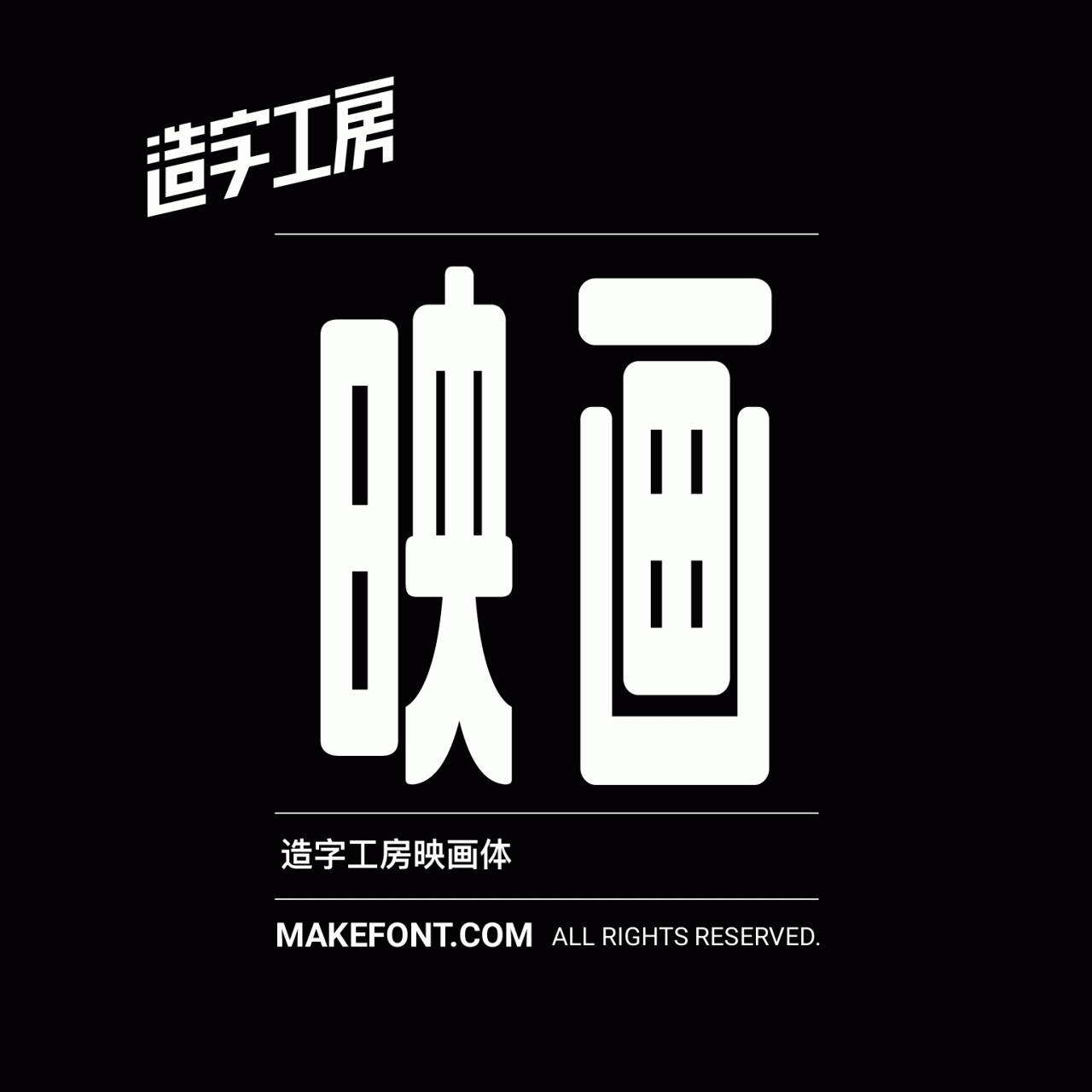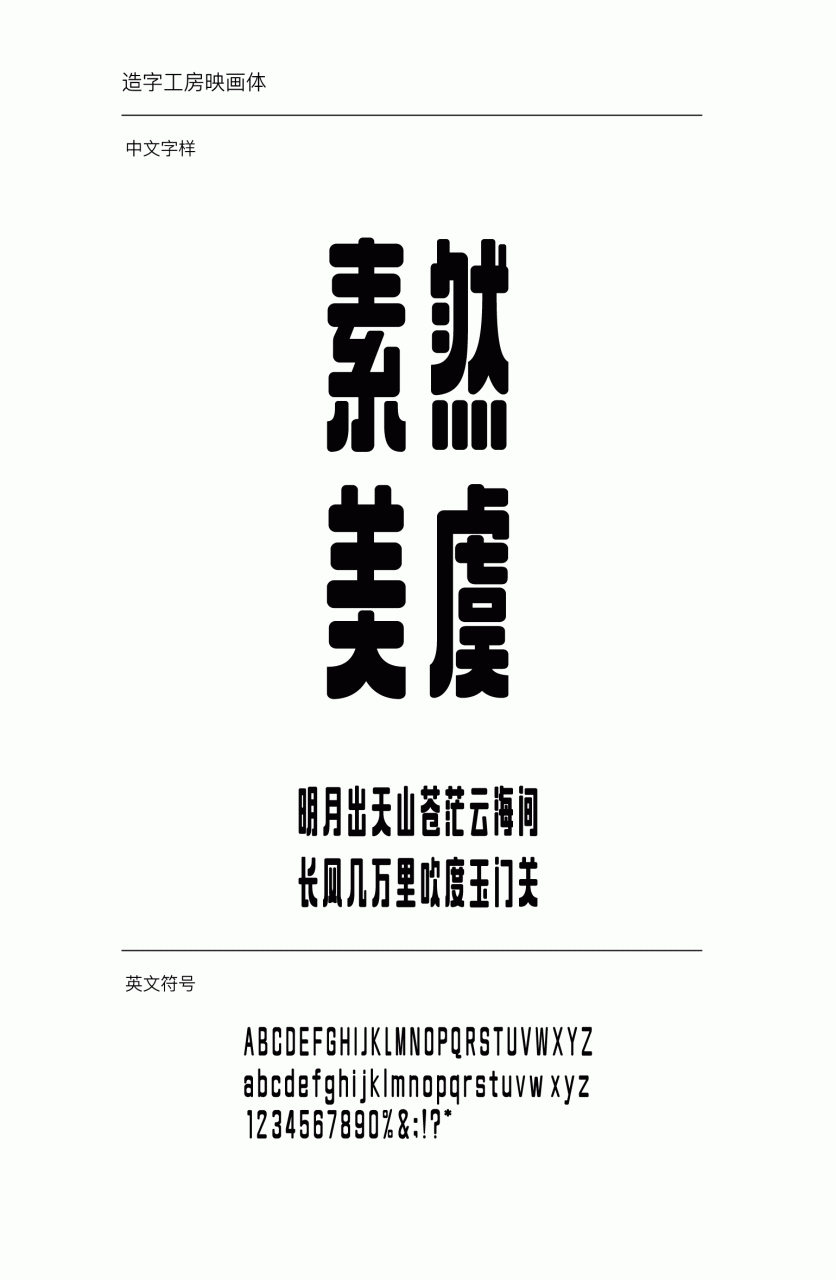
造字工房映画体源于民国时期手绘广告字形,汲取民国字形横粗竖细、重心偏高的特点,细长圆润的笔画让字形更加个性十足,具有很强时代气息,其形变幻灵动,结构呼应一致,字与字之间透露出婀娜窈窕之感,极其符合现代审美的多元化设计应用的需求。是一款诙谐有趣且又不失创新的一款全新字体。适用于大标题及个性品牌设计推广等环境。